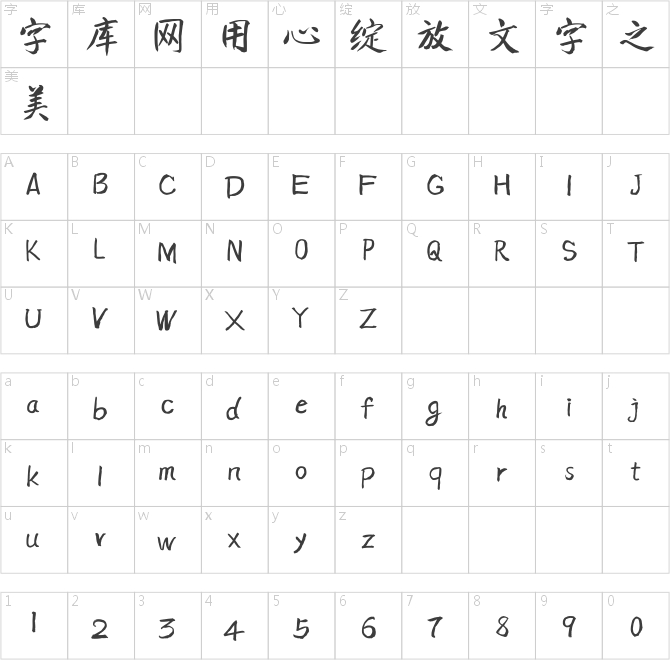
字体名称: 庞门正道真贵楷
庞门正道真贵楷体
庞门正道真贵楷体介绍
hi 下载了《庞门正道真贵楷》的你,首先恭喜你很有眼光。
这款字体由《庞门正道》设计公众号号主阿门的父亲庞真贵老先生,于76岁高龄历时9个月书写制作而成,适用于中国风等商用画面设计配搭。
庞门正道真贵楷体字体字库是一款让人赏心悦目、百看不厌的中文字体,适合各类广告和产品包装设计应用,字体大小8.26MB,格式为ttf字体,上传用户是多拉MO,作者/版权方为庞门正道